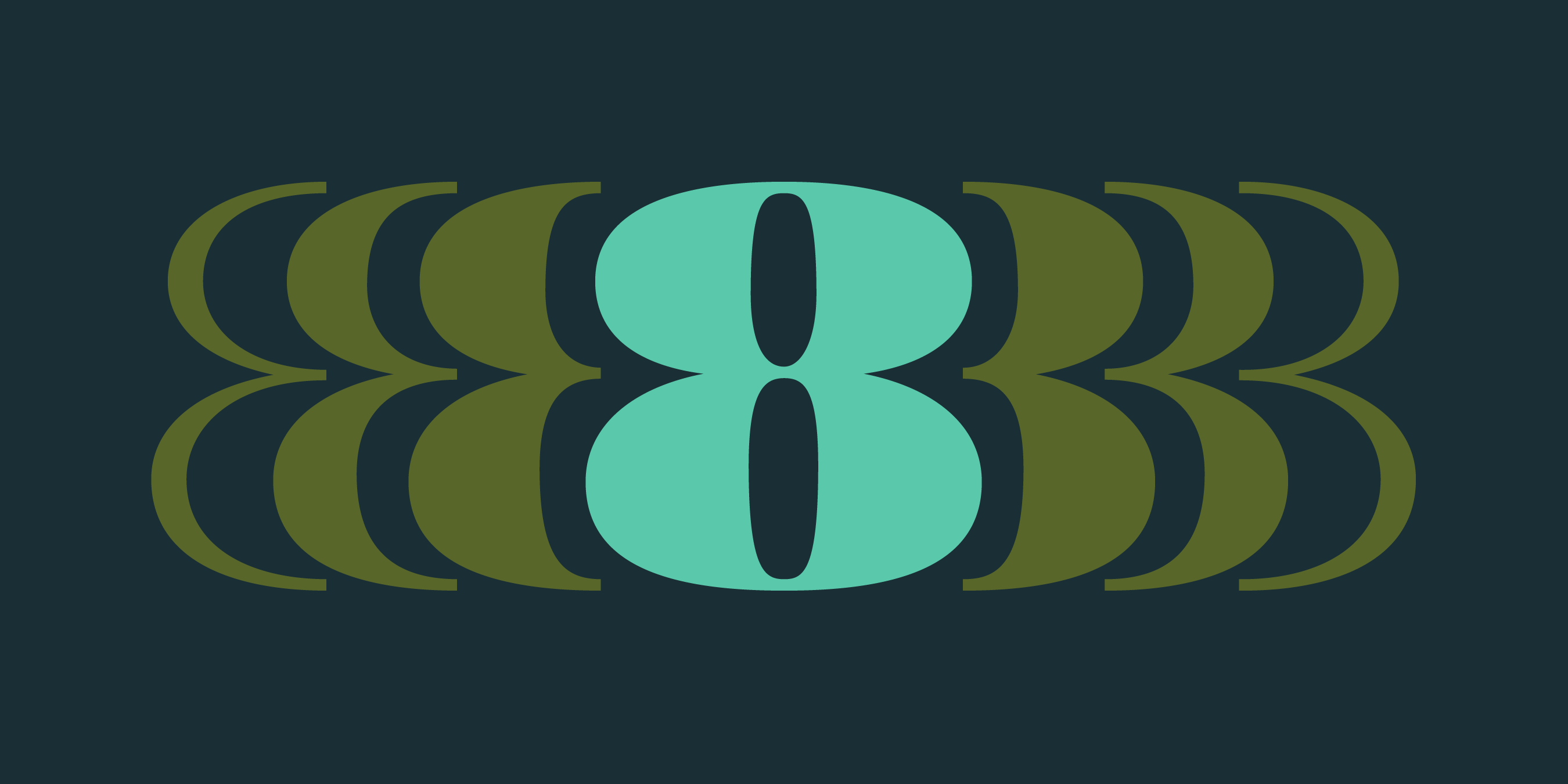
Fuentes sofisticadas: una guía tipográfica
Sophisticated Fonts, A Typography Guide
Las fuentes sofisticadas son a menudo lo que la gente quiere decir cuando habla de fuentes elegantes, pero con una diferencia: las fuentes sofisticadas tienden a parecer un poco menos convencionales, con detalles más atrevidos que las distinguen. En el diseño gráfico, ya sea que esté creando un libro, un recurso para las redes sociales o un estilo de marca, los componentes básicos del diseño incluyen el diseño (cómo se estructuran los elementos en una cuadrícula), los colores, los tipos de letra (fuentes) y los elementos visuales como ilustraciones, fotos o visualización de datos. Los elementos decorativos, como los avisos ("Comprar ahora" o "Nuevo"), a menudo agregan énfasis.
Sin embargo, las fuentes y la tipografía suelen subestimarse. Los nuevos diseñadores o vendedores, que suelen desempeñar múltiples funciones y crear sus propios recursos de marketing, pueden pasar por alto las fuentes como base de un diseño memorable. Las fuentes tienen una forma de incrustarse en el subconsciente, dando forma a la sensación que transmite un diseño sin que la gente se dé cuenta. Invertir en una tipografía distintiva es una de las formas más rentables de destacar. A diferencia de las ilustraciones o fotografías personalizadas, que pueden ser caras, la tipografía sofisticada puede tomar la delantera, actuando como un elemento visual y narrativo. La tipografía adecuada, combinada con diseños y tamaños de texto bien pensados, puede llevar el peso de todo un diseño.
Veamos cómo los tipos de letra pueden crear sofisticación de diferentes maneras.
Ques, fuente humanista moderna para la elegancia Fuente sans elegante y moderna de Scal Fuente natural y sofisticada de Kijs
1. Características de las fuentes sofisticadas
El concepto básico de fuentes sofisticadas se alinea estrechamente con el de fuentes elegantes . Incluyen pesos ligeros, fuentes serif bellamente elaboradas, sans-serif minimalistas, fuentes de contraste e incluso estilos elegantes escritos a mano. Sin embargo, las fuentes sofisticadas a menudo presentan pequeños detalles que solo los entendidos aprecian. Por ejemplo, algunas fuentes sofisticadas tienen contadores internos redondeados para una sensación más natural, como nuestra fuente "Kijs". Otras tienen terminales ligeramente más nítidas, como "Scal", que ofrece un aspecto más moderno y actualizado que recuerda a estilos clásicos como Futura. Estos matices sutiles hacen que las fuentes sofisticadas no solo sean visualmente atractivas, sino también ricas en carácter y profundidad.
2. Contexto histórico
Las fuentes sofisticadas tienen una historia rica y variada que refleja la evolución de las tendencias de diseño y los avances tecnológicos:
• Antigüedad clásica: Las raíces de las fuentes sofisticadas se remontan a las inscripciones romanas, que presentaban elegantes fuentes serif diseñadas para facilitar la lectura y el atractivo estético.
• Renacimiento y Barroco: Durante estos períodos, el diseño tipográfico se volvió más refinado, con fuentes como Garamond y Baskerville que personificaban la sofisticación y la elegancia.
• Era Moderna: En el siglo XX, diseñadores como Adrian Frutiger y Hermann Zapf traspasaron los límites de la tipografía y crearon fuentes atemporales que siguen siendo populares en la actualidad. El movimiento Bauhaus, con su énfasis en la función y la simplicidad, también influyó significativamente en la tipografía moderna.
Estas influencias históricas han dado forma a las sofisticadas fuentes que conocemos hoy, combinando principios de diseño clásicos con la estética moderna.
Fuente serif sofisticada y modernaFuente serif cálida Edde
3. Dónde utilizar fuentes sofisticadas
Las fuentes sofisticadas expresan un tono de comunicación o de marca que literalmente significa "refinado". El tono de una marca surge del posicionamiento de la misma, de "qué" quiere que el lector o el cliente digan sobre usted cuando no está presente. Por lo tanto, si lo que quiere comunicar en su diseño es "dar una impresión de refinamiento", puede aplicar un enfoque "sofisticado" a cualquiera de los siguientes elementos de diseño:
• Branding y logotipos: Las fuentes sofisticadas añaden un toque de lujo y profesionalismo, lo que las hace ideales para marcas y empresas de alta gama que desean transmitir una imagen refinada.
• Diseño editorial: perfecto para revistas, folletos y libros, donde la legibilidad y la elegancia son primordiales. “Mod” y “Edde” se integran fácilmente en marcas sofisticadas, mejorando la legibilidad y manteniendo una estética moderna.
• Invitaciones y papelería: Aportan un toque de sofisticación personal a las invitaciones de boda, tarjetas de visita y papelería personal.
• Diseño web: Las fuentes sofisticadas mejoran la experiencia del usuario al proporcionar un aspecto limpio y profesional que es adecuado para sitios web e interfaces digitales cuyo tono de marca alude al refinamiento.
• Desarrollo de juegos: Las fuentes de burbujas como “Skay”, incluso en sus pesos más livianos para mayor elegancia, pueden agregar personalidad a los títulos de los juegos y al texto del juego, haciendo que la experiencia general sea más inmersiva.
Estos ejemplos demuestran cómo las fuentes sofisticadas pueden mejorar varios tipos de proyectos, agregando un nivel de refinamiento y claridad que es difícil de lograr con tipografías más genéricas.
Fuente femenina Rozi
4. De nuestra colección de fuentes
En Mojomox Font Shop, ofrecemos una variada colección de fuentes sofisticadas, cada una con características únicas que satisfacen diversas necesidades de diseño. A continuación, se muestran algunos de los elementos destacados de nuestra colección:
Fuentes Serif:
• Bauhaus Mod: Mod es una tipografía serif moderna perfecta para marcas de moda y belleza. Tiene trazos fuertes y definidos con terminales parcialmente redondeados para una calidad personal. Ver Mod
• Rozi: Rozi es una fuente serif hermosa y fuerte para marcas y títulos, con un estilo elegante en estilos finos y llamativos. Rozi tiene ligaduras y letras alternativas, como dos o más opciones para los glifos A, B, C, G, O y R, para personalizar los diseños. Ver Rozi
• Kijs: ideal para marcas y titulares, Bauhaus Kijs es una fuente natural con serifas, perfecta para marcas de belleza, moda y alimentación de espíritu libre. Kijs tiene contrafuertes entintados y presenta una i y una j cursivas para una personalidad creativa y terrenal. Kijs tiene terminales redondeadas y muchos diseños de letras alternativos para variaciones de diseño personalizables con un toque orgánico. Ver Kijs
Fuentes Sans-Serif:
• Scal: tipografía geométrica minimalista para marcas, títulos y textos principales. Scal es una fuente puntiaguda clásica similar a los estilos tipo Futura con puntas afiladas pero con un toque moderno. Scal contrasta letras anchas con delgadas para una calidad de diseño elegante, combinada con terminales nítidas y distintivas, perfecta para marcas de belleza, moda y publicaciones. Aspecto elegante y sofisticado en estilos más claros y más divertido en estilos más atrevidos. Ver Scal
• Acme en pesos más ligeros: Bauhaus Acme es una fuente sans-serif limpia y fresca. Es la tipografía perfecta para marcas de tecnología y diseño. Nítida y moderna con un toque amigable. Acme tiene terminales ligeramente alargadas e inclinadas, lo que le da un aspecto contemporáneo pero acogedor. Ver Acme
Roma elegante contraste sin
Fuentes de contraste:
• Roma: Roma es una tipografía humanista de contraste con un marco geométrico diseñado para lucir limpio y minimalista. Esta fuente es perfecta para marcas de moda, belleza y bienestar. Ver Roma
• BH Soft: Bauhaus Soft es una tipografía serif amigable. Tiene un marco geométrico con terminaciones parcialmente redondeadas. Esta fuente es perfecta para marcas que desean comunicar elegancia con un tono accesible. Ver BH Soft
• Chez: Chez es una fuente redondeada, moderna y de alto contraste, perfecta para marcas de belleza, moda y alimentos. Ver Chez
• Ques: Ques es una fuente sans-serif humanista ancha que presenta trazos ensanchados para una calidad personal, casi serif. Su aspecto caligráfico y su variedad de conjuntos estilísticos la hacen perfecta para tiendas de belleza, moda, floristerías y marcas que desean una combinación de elegancia con clase en un estilo moderno. Ver Ques
Ques, fuente sans-serif de grosor finoFuente manuscrita elegante y ligera con encaje
Fuentes escritas a mano:
• Lace en grosores ligeros: Lace es una tipografía moderna diseñada para crear letras de marca modernas. Si bien tiene un carácter manuscrito, sus trazos son uniformes y solo varían con el grosor de la fuente. Lace es perfecta para marcas de restaurantes y belleza, ya que muestra un aspecto moderno pero personal. Ver Lace
5. Consejos para elegir la fuente sofisticada adecuada
A continuación se ofrecen algunos consejos que le ayudarán a elegir la fuente sofisticada adecuada para su proyecto:
• Propósito y contexto: considere las necesidades específicas de su proyecto. Una fuente serif puede ser más adecuada para invitaciones formales o marcas de lujo, mientras que una fuente sans-serif puede funcionar mejor para un sitio web moderno o una marca tecnológica.
• Legibilidad: asegúrese de que la fuente sea legible en distintos tamaños. Las fuentes sofisticadas deben mantener la claridad, especialmente en el cuerpo del texto, sin sacrificar su apariencia elegante.
• Combinación de fuentes: al combinar fuentes, elija tipos de letra complementarios que realcen las cualidades de cada uno. Por ejemplo, combinar una fuente serif definida como “Rozi” con una sans-serif minimalista como “Scal” puede crear un diseño equilibrado y cohesivo.
• Grosores y estilos de fuentes: utilice distintos grosores y estilos de fuentes para agregar jerarquía y énfasis a su diseño. Las fuentes sofisticadas con distintos grosores, como las de nuestra colección, ofrecen flexibilidad para distintos elementos de diseño.
• Flexibilidad de diseño: busque fuentes con glifos y ligaduras alternativas. Estas características brindan una mayor flexibilidad de diseño, lo que le permite personalizar la tipografía para que se adapte mejor a la personalidad de su marca.
6. Tendencias futuras en fuentes sofisticadas
La tipografía evoluciona constantemente y las fuentes sofisticadas no son la excepción. A continuación, se presentan algunas tendencias emergentes a las que hay que prestar atención:
• Minimalismo en el diseño: coloque las fuentes en el centro de sus diseños eliminando elementos innecesarios. Trabaje con tamaños y diseños de fuentes para crear gráficos interesantes y sofisticados que permitan que los detalles de las fuentes destaquen.
• Maximalismo en el diseño: esto puede parecer una contradicción, pero implica exagerar el minimalismo con mucho color, muchos grosores y maximizar las combinaciones de fuentes. Siga las mismas pautas de diseño que el minimalismo, pero haga que su diseño destaque con más elementos, creando un aspecto audaz y dinámico.
• Diseño experimental: juegue con los grosores de las fuentes, el espaciado y los glifos alternativos para personalizar los diseños. Utilice nuestras grandes familias de fuentes con muchos glifos alternativos para crear una tipografía única y personalizada.
Estas tendencias resaltan la naturaleza dinámica de la tipografía y la importancia continua de las fuentes sofisticadas para crear diseños impactantes y refinados.